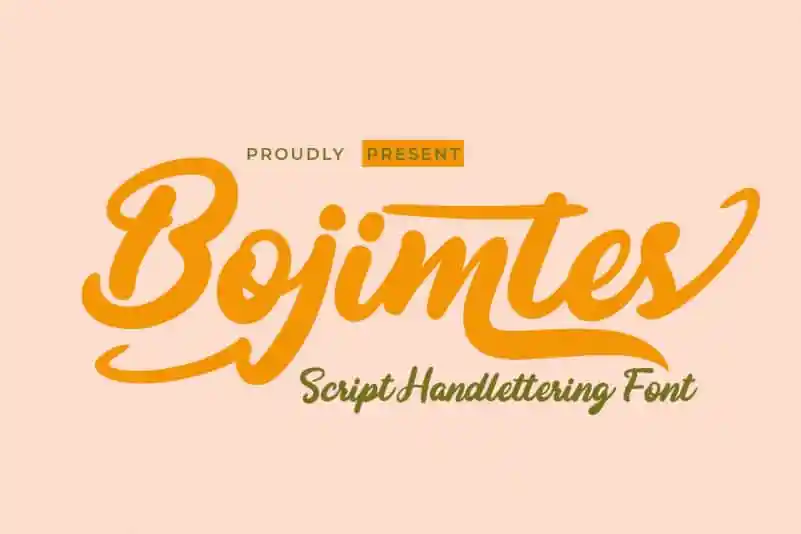
Bojimtes Script Font – Download Grátis
Bojimtes Script Font é uma fonte tipográfica que oferece belas tipografias abstratas para diversos projetos de design. Esta fonte está perfeitamente adaptada tanto para projetos gerais como específicos, como convites de casamento, designs com citações, criação de marcas sociais e empresariais, anúncios, logotipos, banners promocionais alimentícios ou bebidas, textos, painéis, assinaturas, e qualquer projeto que exija um arquétipo manuscrito. Ideal para quem procura uma fonte elegante e versátil que pode personalizar várias camadas de design gráfico, Bojimtes Script Font é o elemento perfeito para seus projetos. Como criado pelo designer twinletter, a fonte oferece harmonia e beleza tanto visual quanto funcional, tornando-a um recurso indispensável para todos aqueles que buscam uma adição atraente à sua biblioteca de fontes.